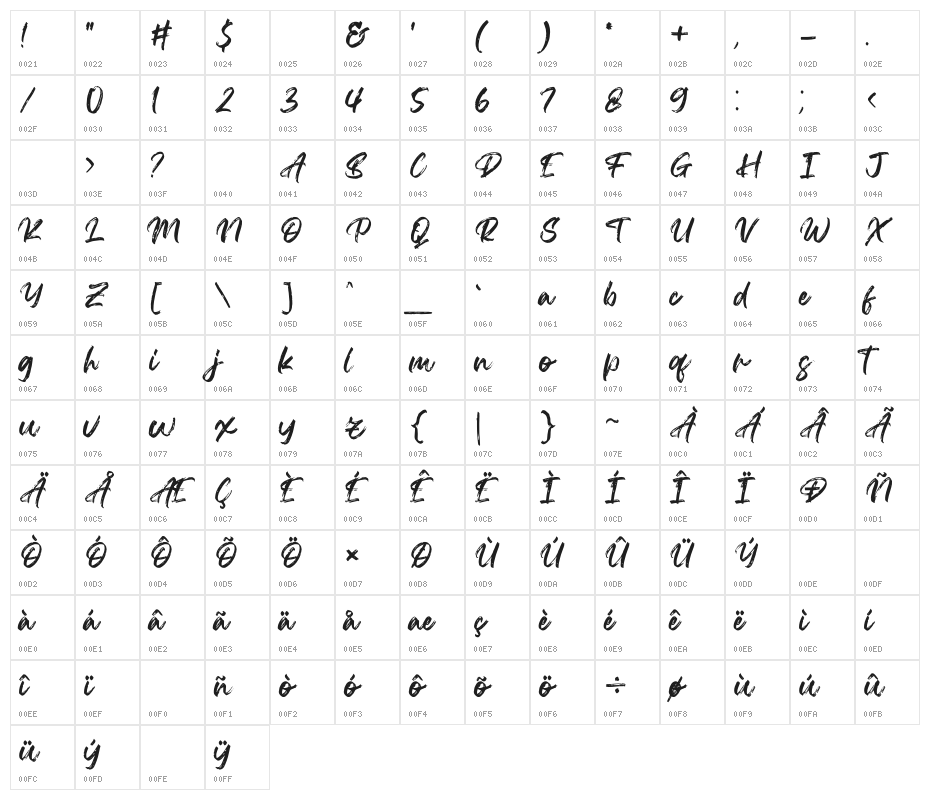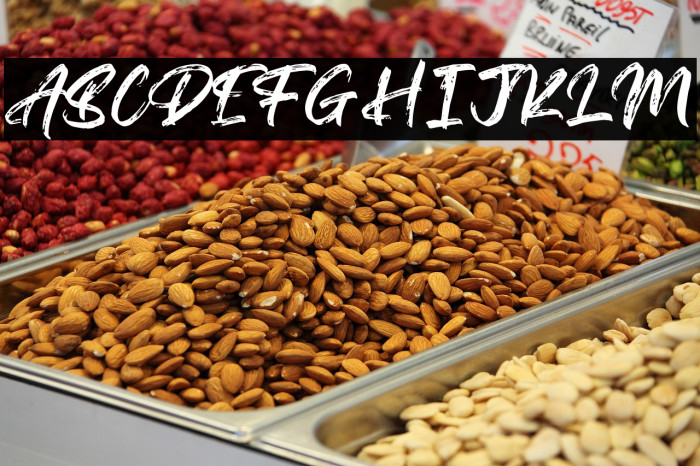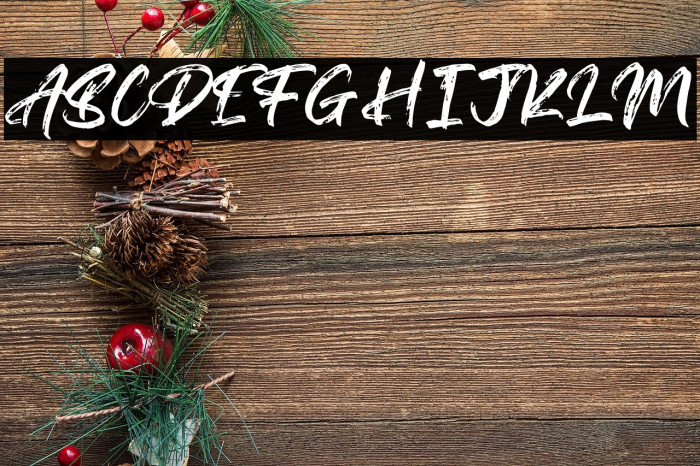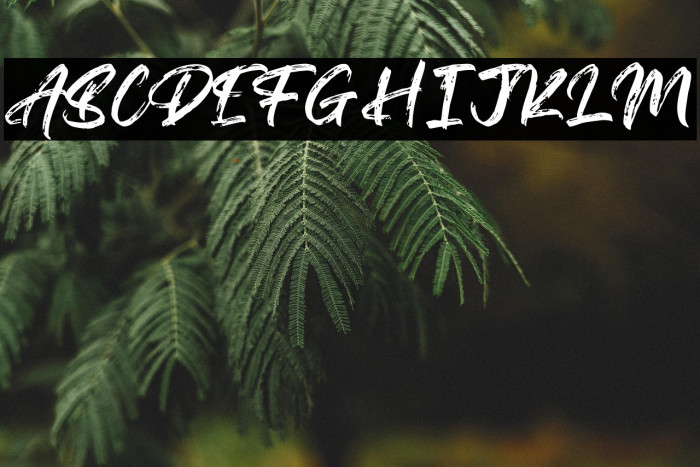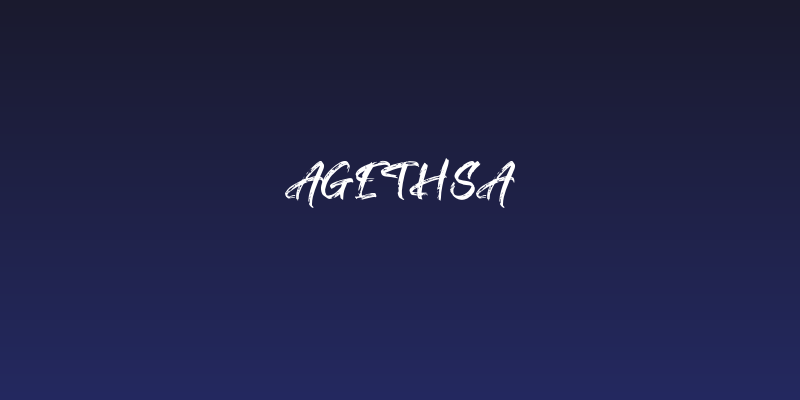
Agethsa Font
| Vorgeschlagene Projekte | Ideal for branding, posters, album covers, and creative design projects that require a bold, artistic touch. |